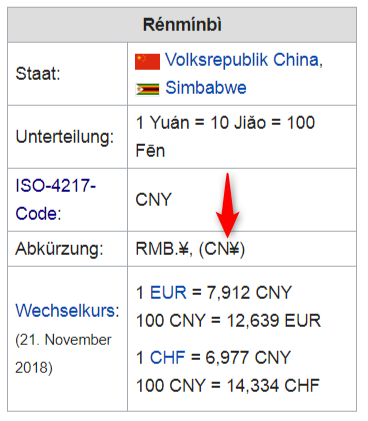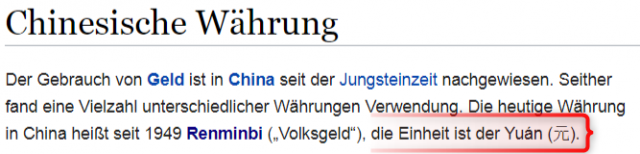
Und hier das Ergebnis bei CorelDraw 2014:
vielleicht sollte man die Nutso so umbauen, dass daraus eine Osterbar mit leichter schreibweise wird. Nur mal so als Idee.
Muss mal bei den Entwicklern anfragen, ob man seine schriften mit disen features ausstatten darf, ich vermute mal ja.
Wie ja oben schon angemerkt ist das etwas tricky und funktioniert auch nicht überall.
Werde den waagerechten Bruchstrich wohl etwas dünner machen...
bei Serifen-Schriften sieht es aus als würde der Bruchstrich so dick sein wie der "Fuss" von der grossen 1
Da ja die Osterbar keine ist weiss ich nicht an welche Strichstärke man sich orientiert.
Müsste man im Netz mal schauen ob es andere Beispiele gibt.
@catfonts Der richtige Begriif scheint fonts with stacked fraction zu sein. da findet man auch Beispiele in der Bildersuche (Google) für sanserif Schriften
:tuschel: $euro wäre vielleicht noch ein praktischer Code für Leute ohne €-Tastatur.
... und für die mit ganz alten Zeichensätzen ohne € drin auch noch ein $FRZ :mrgreen:
Die nigerianische Naira ₦ NGN scheint noch zu fehlen.
(Und dass du keinen ₰ eingebaut hast, wundert mich dann doch. :-P)
Stimmt, war nicht in meiner Liste - und von historischen hatte ich ja Abstand genommen, drum eben keine RM
$CNY  steht laut PDF nur ¥  ( laut wiki müsste es CN¥ heissen) wenn das einzeln steht könnte es mit dem japanischen Yen verwechselt werden.
ich staune, dass die nicht gleich das Zeichen hier genommen haben  schaut ja fasst aus wie ein π mit strich darüber.
Die Abkürzung CN¥ ist dann richtig, wenn eine Verwechselungsgefahr besteht, z.B. auf einer Wechselkursliste, auf der dann nur die Abkürzungen genannt sind, das ist ja nicht anders mit den ganzen $ - Währungen.
Ist es hingegen klar. das Chinas Währung gemeint ist, steht nur ¥:
"Ich habe in Shenzhen für dieses Handy nur ¥ 650.- bezahlt"  - da wird niemand annehmen, das da japanische Yen gemeint sind. da es selbst in China kaum ein Handy für 5 Euro geben wird :-).
Aber man muss eben wirklich einen deutlichen Unterschied zwischen Festland-chinesischem Geld haben, und dem der "Abtrünnigen Proviz", also der Republik China, auch Taiwan, oder auch als Formosa bekannt, die eben im nicht Latein-schriftlichen das Zeichen 元 verwenden.
yuan (jap. [y]en) bezeichnet eigentlich keine Währung, sondern ist eher so etwas wie ein Zählwort (evtl. vergleichbar mit "Taler"). So steht sowohl auf der Taiwan- als auch auf der VR-Note nach der Zahl das Zeichen für yuan (einmal lang: 圓, einmal kurz:  元 [nicht zu verwechseln mit "rund" 圓 > 圆], – auch in Japan wurde ursprünglich das Langzeichen 圓 benutzt, heute das jap. Kurzzeichen 円).
Ist also relativ eindeutig:
元 – VR China
圓 – Taiwan
円– Japan
PS: In Hongkong ist die Währung der HK$, auf den Scheinen steht ebenfalls 圓.
Jetzt fehlt nur noch , dass das Zeichen ¥ eigentlich EVP bedeutet ;-) weil das da überall bei den Preisauszeichnungen steht.
Jetzt fehlt nur noch , dass das Zeichen ¥ eigentlich EVP bedeutet
😅 EVP  MDN
ja :-)
nur finden mit font-editor ist schon ein wenig ein foul
das war harte Arbeit bei so viel Sachen drin😉. Hab nur alte mit neuer Version verglichen, wo die Zahlenwerte sich ändern bin ich rein. In den Glyphen kann man dich nicht entdecken. nicht mal unter ##pw
nur finden mit font-editor ist schon ein wenig ein foul
Aber nur durch Ausprobieren hätte diese Zeichenfolge ja nie wer gefunden. Und nicht gefundene Ostereier fangen irgendwann an zu müffeln! ;-)
@catfonts Hallo Peter ich bin gerade im HighLogic Form (FontDesigner) hab das problem mit den Brüchen dort noch mal angesprochen. Darf ich die Osterbar verlinken? vielleicht bekommt man ja doch eine ellegantere lösung hin um diese Brüche einfacher zu setzen